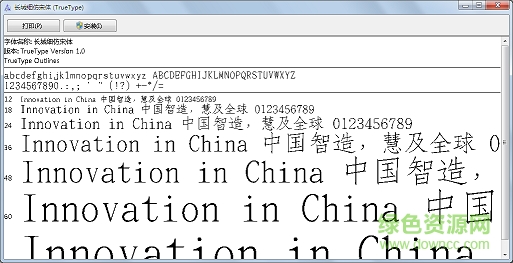
gbnansung light字體又叫長城細(xì)仿宋體字體,字形清秀,筆畫細(xì)挺,線條流暢,嚴(yán)謹(jǐn)有不失風(fēng)韻,令人耳目一新,歡迎大家在綠色資源網(wǎng)下載!
1.擁有楷體的筆型,這使仿宋體較像手書體而不是宋體所屬的印刷體。
2.各筆劃等粗,不似宋體般的橫細(xì)直粗。
3.字體較為瘦長。